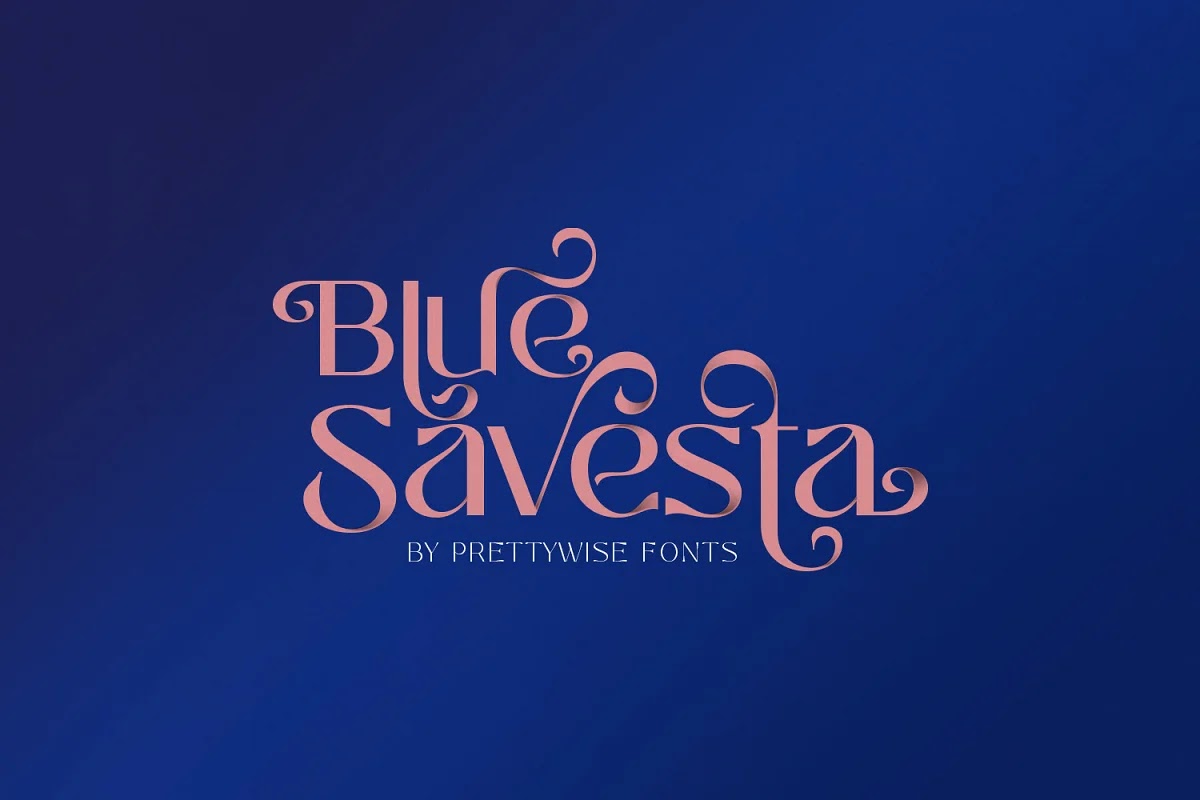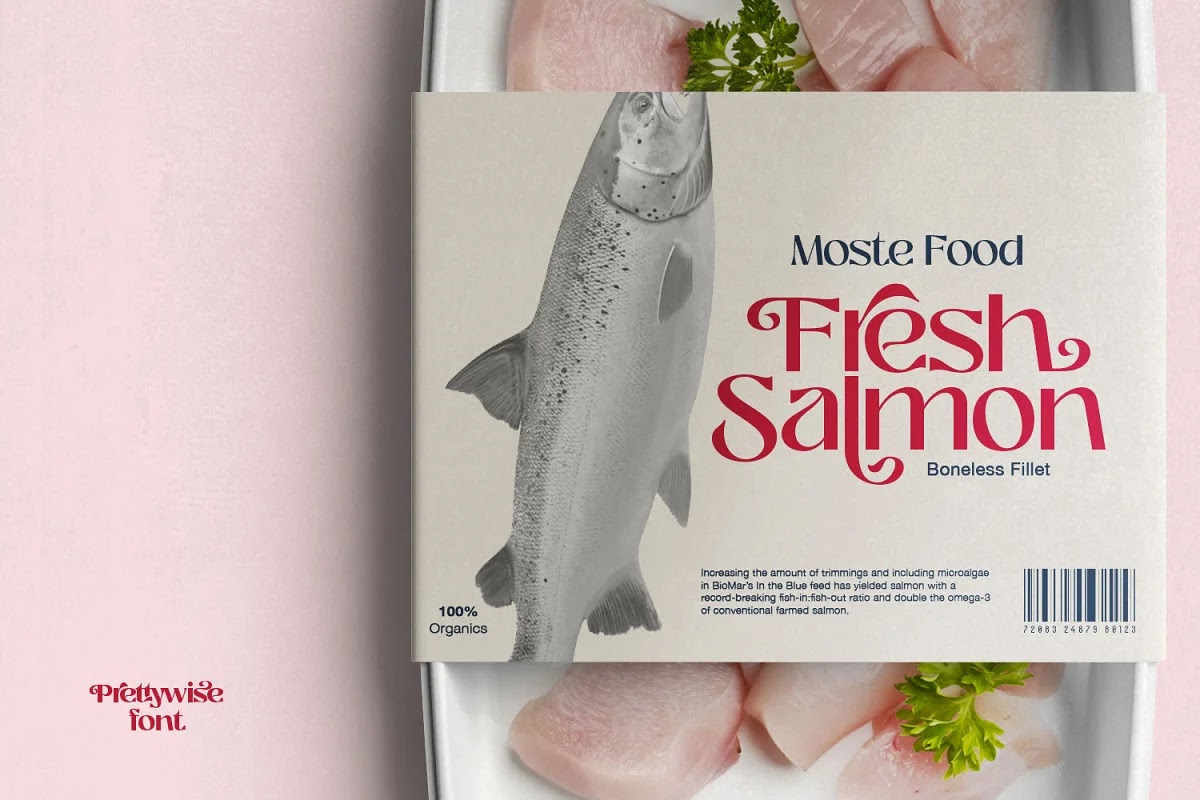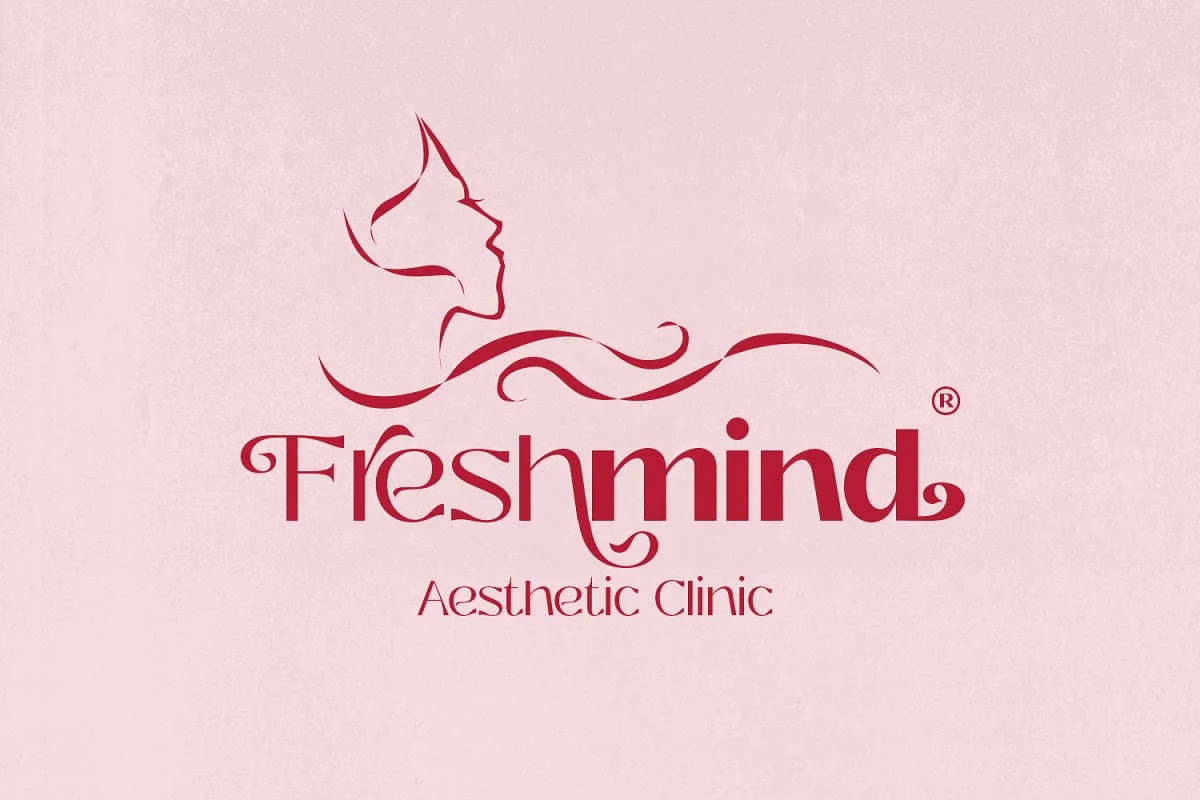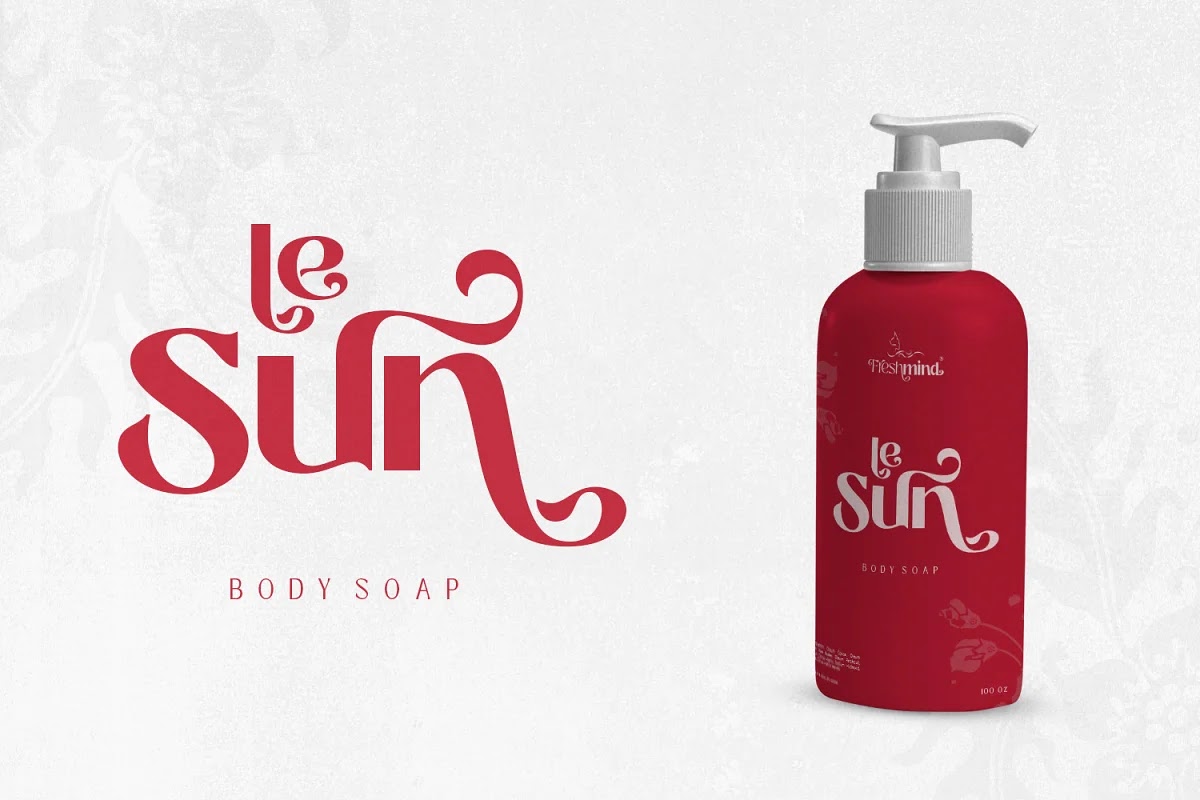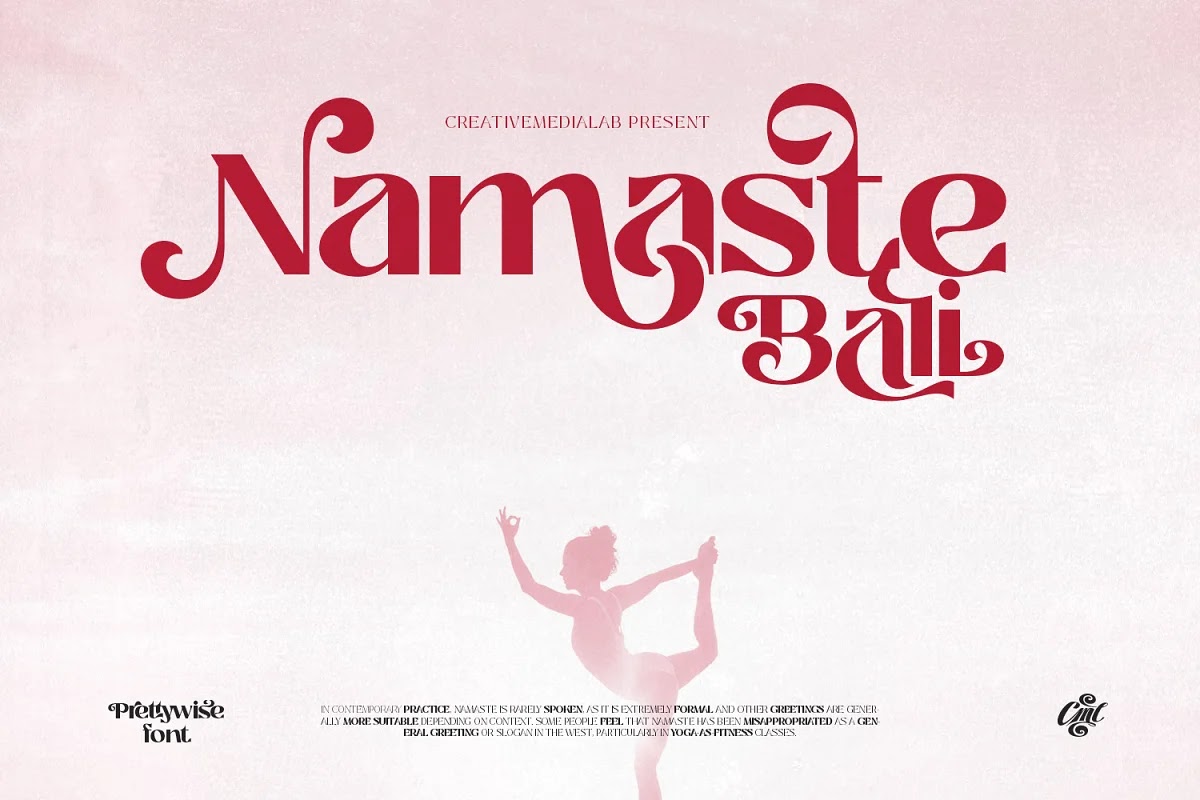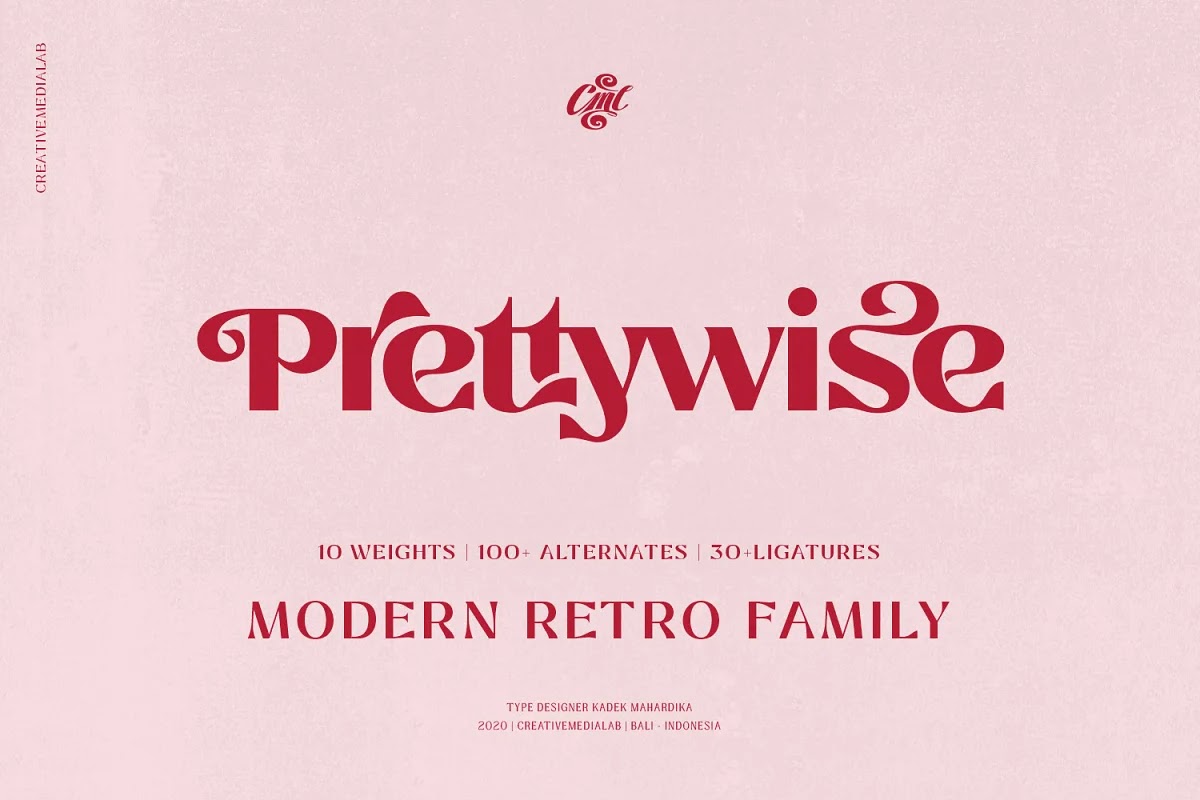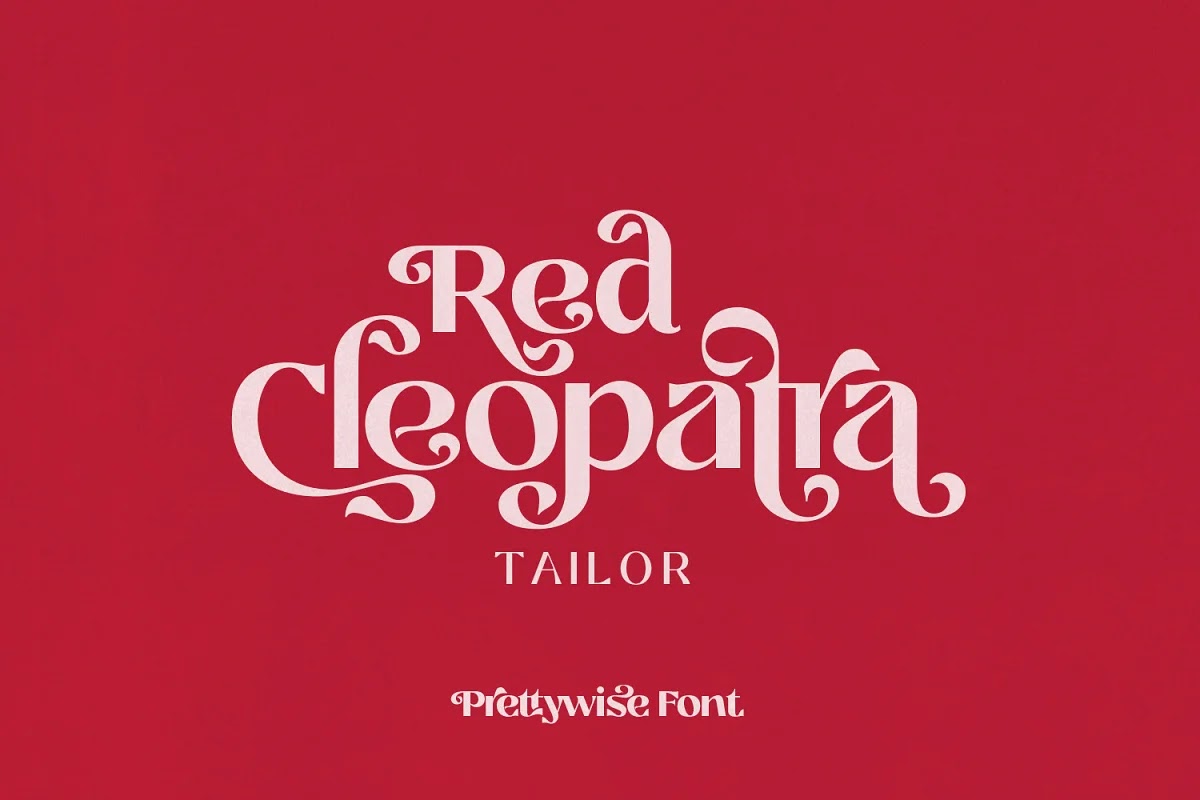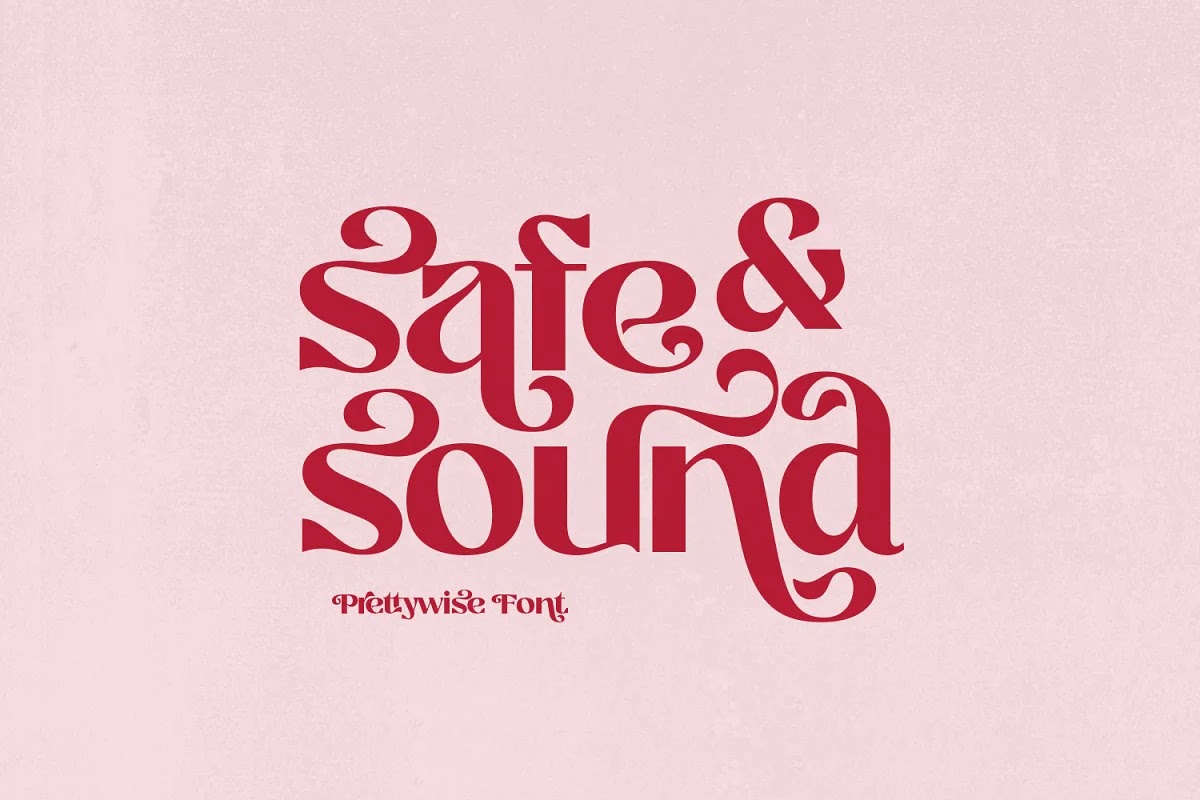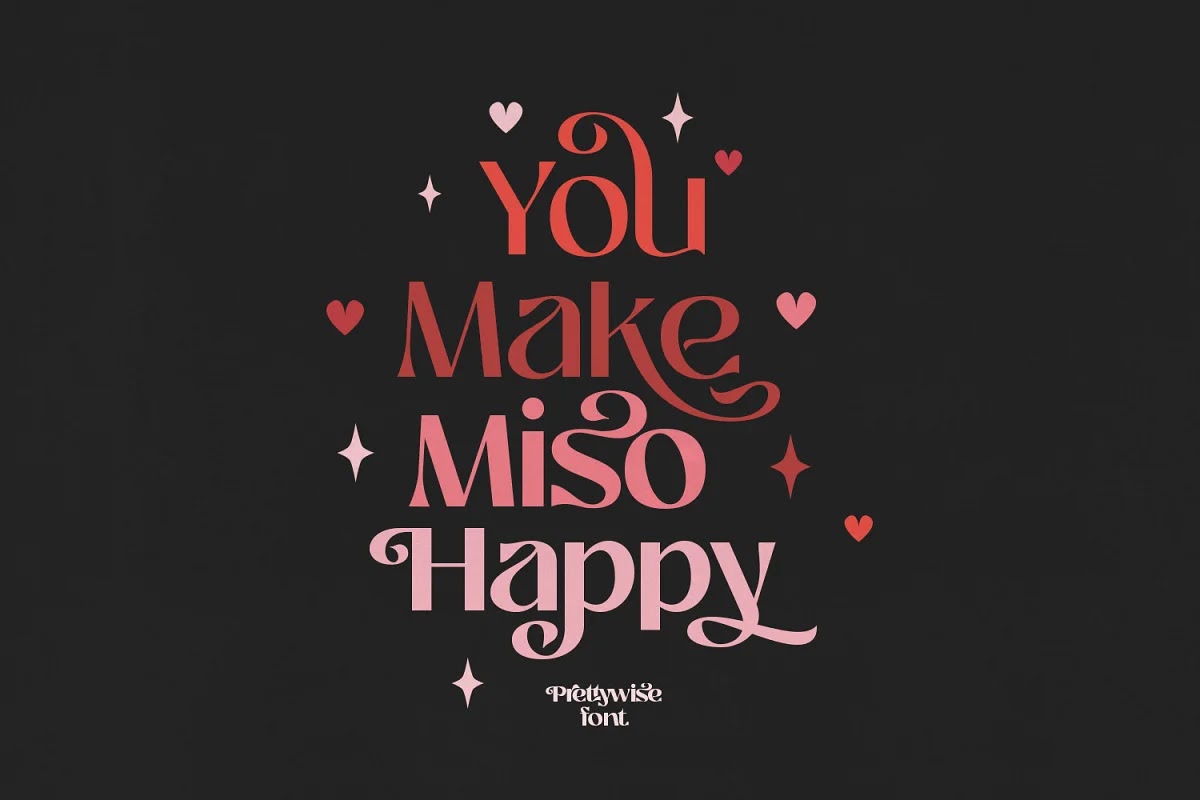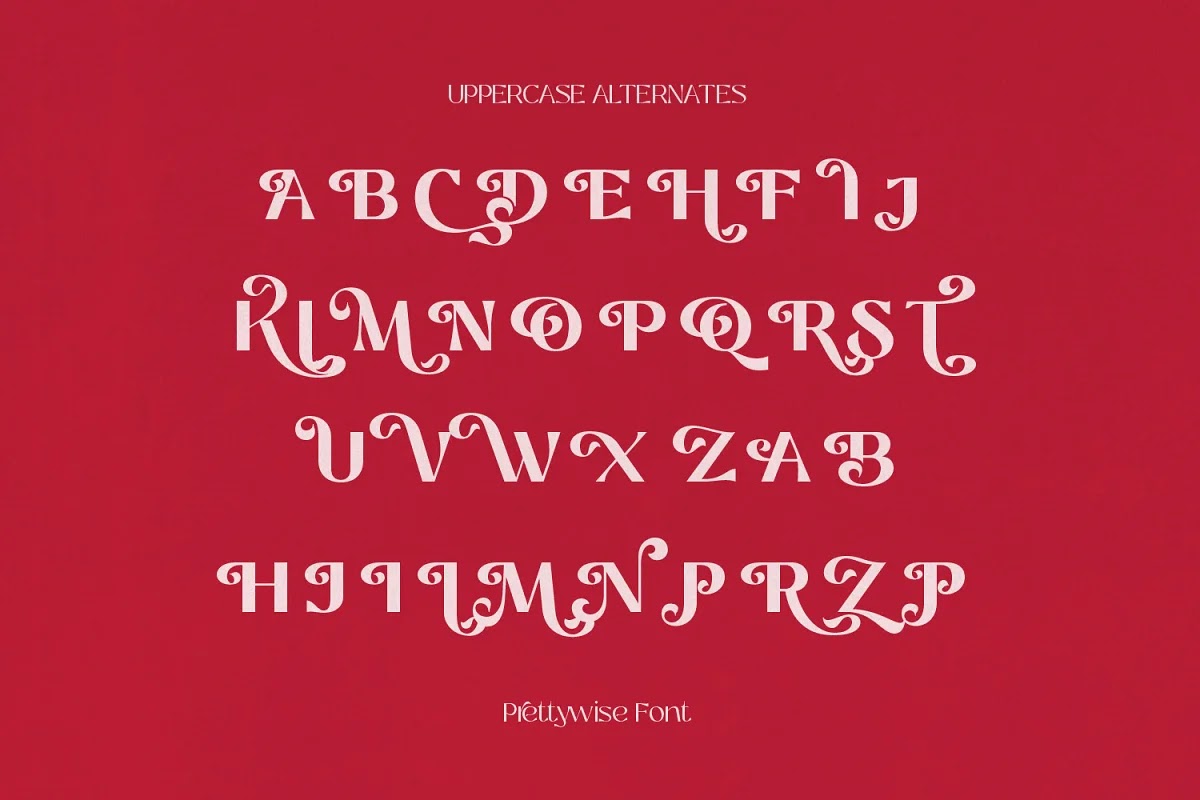
Prettywise – Modern Retro FamilyMột bộ font độc đáo và đẹp mắt bao gồm hơn 30 chữ ghép và hơn 100 chữ thay thế để cho bạn thoải mái kết hợp mang đến những thiết kế hoàn hảo.
Bộ font bao gồm hơn 10 kiểu, thích hợp để sử dụng cho nhiều thiết kế như tạp chí, thiết kế web, banner, poster nhạc, poster phim, bao bì, font cũng phù hợp với các thiết kế cổ điển và hiện đại.